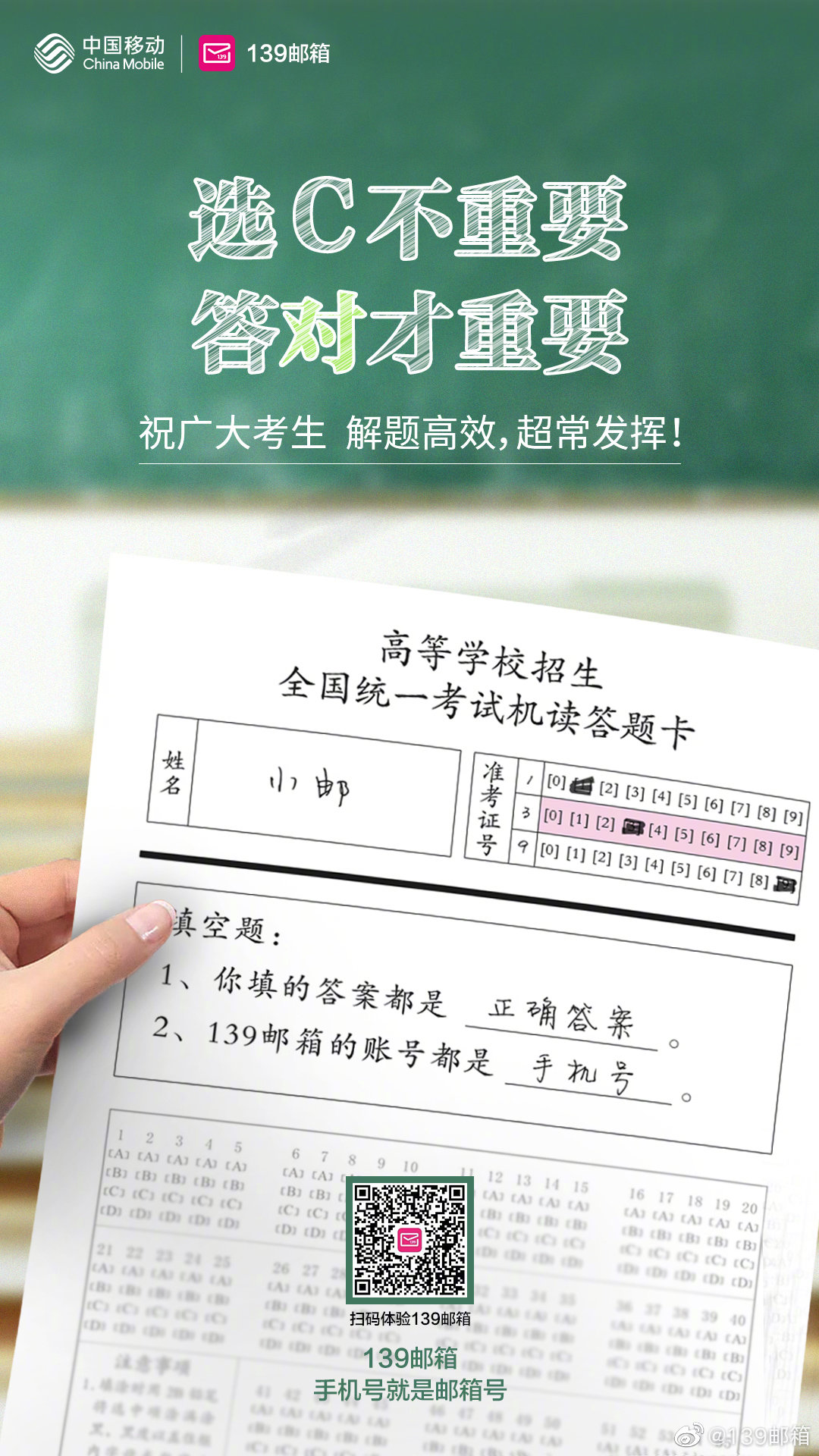
方正楷体
方正字库
楷书
方正楷体源于上海印刷技术研究所为铅字印刷设计的“华文楷体”字稿。原“华文楷体”诞生于20世纪40年代,新中国成立后一直是主要使用的铅字楷体。在此期间,上海字模一厂、上海印刷技术研究所等单位进行了数次改良,并添加了简体字。方正楷体的结构秀丽匀称,笔画圆润柔和,横竖笔画的粗细变化不大。这款字体被大量应用于报纸、杂志和书籍中的正文,在教科书中最为常见。